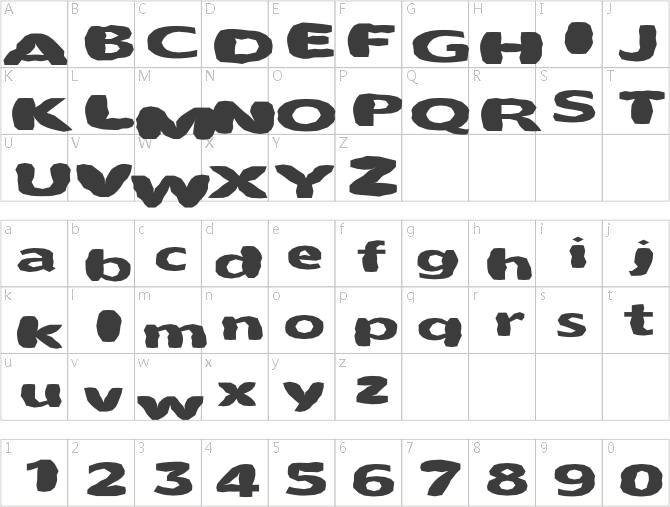
FZ BASIC 55 MANGLED EX 詳情頁(yè)
FZ BASIC 55 MANGLED EX字體字庫(kù)是一款讓人賞心悅目、百看不厭的英文字體,適合各類廣告和產(chǎn)品包裝設(shè)計(jì)應(yīng)用,字體大小0.07MB,格式為ttf字體,上傳用戶是多喝燙水,作者/版權(quán)方為未知